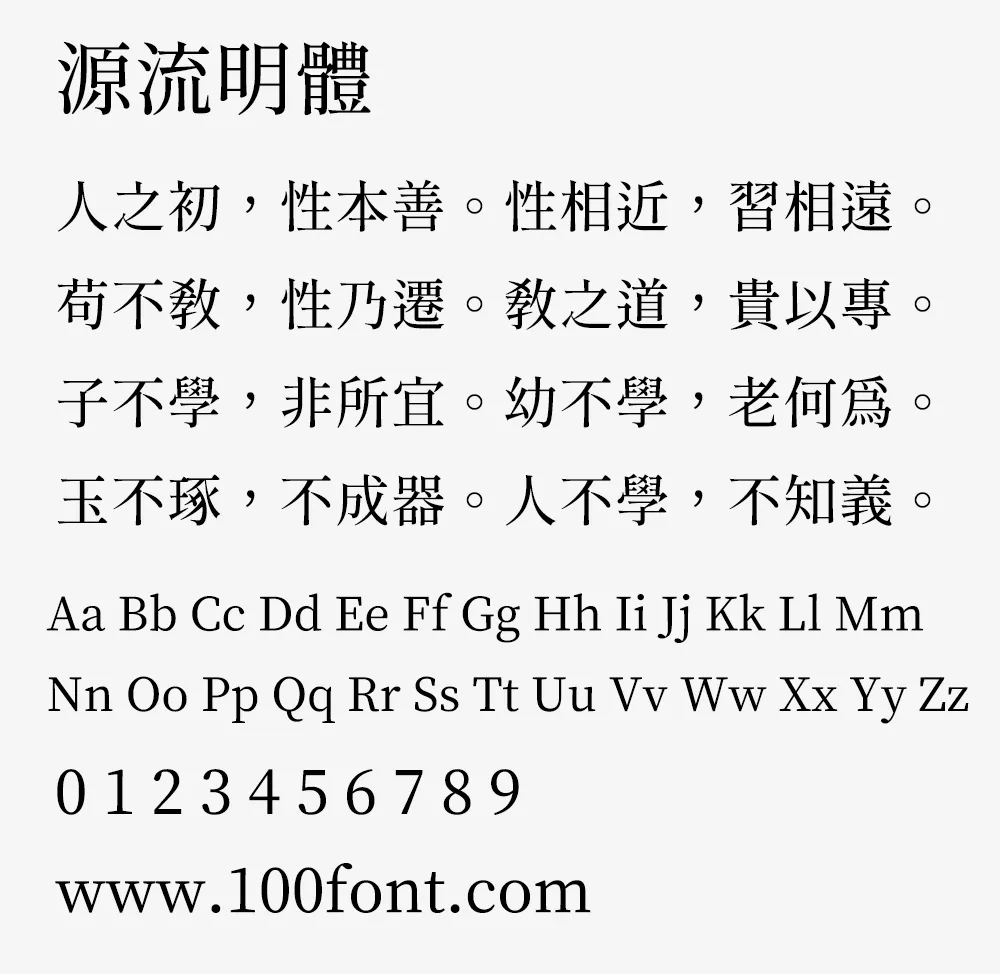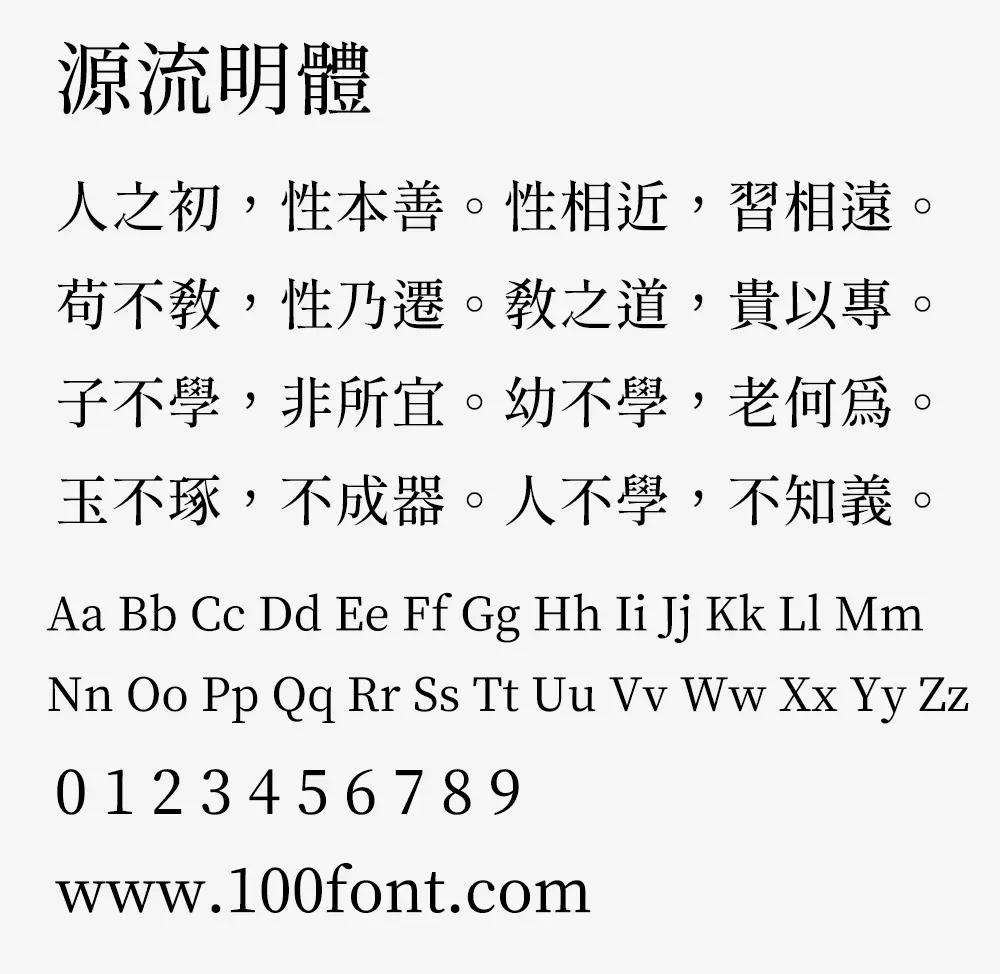
源流明體由臺灣字型社團「字嗨」管理員 But Ko基於“思源宋體的繁體中文字體”修改衍生而來,傳統印刷體風格,筆劃帶有抑揚頓挫情緒的繁體中文字型,字體改造雖以計算機程序自動進行,但在一些細節調整後可以明顯感受出不同效果,源流明體在筆畫上有所調整,使字型看起來更有力道。
注意提醒:這款字體主要適用於繁體中文,雖然也支持簡體中文,但是簡體可能會出現錯別字等情況。